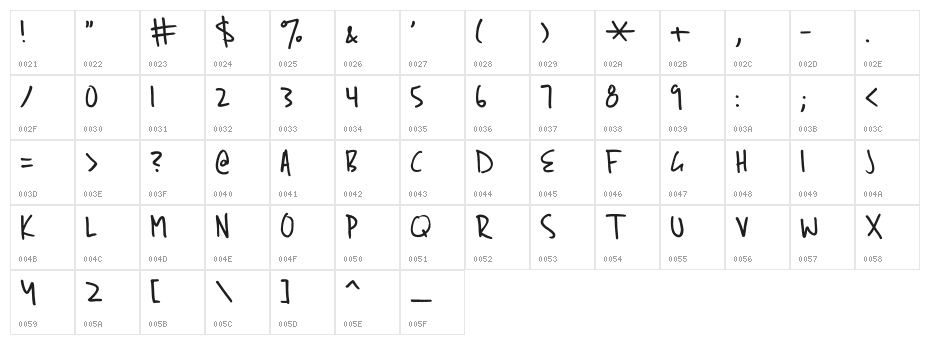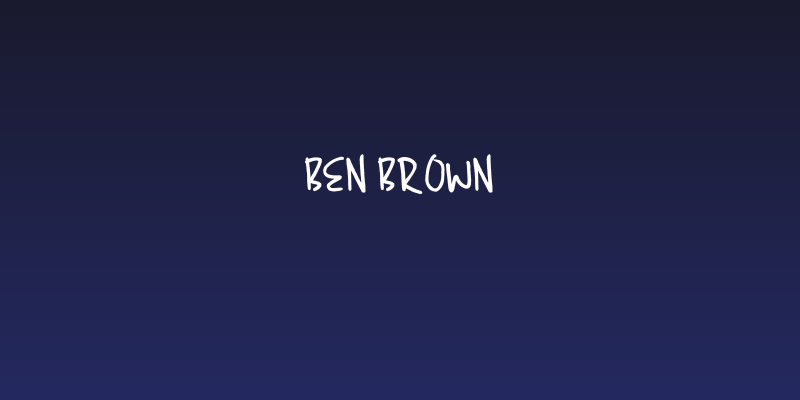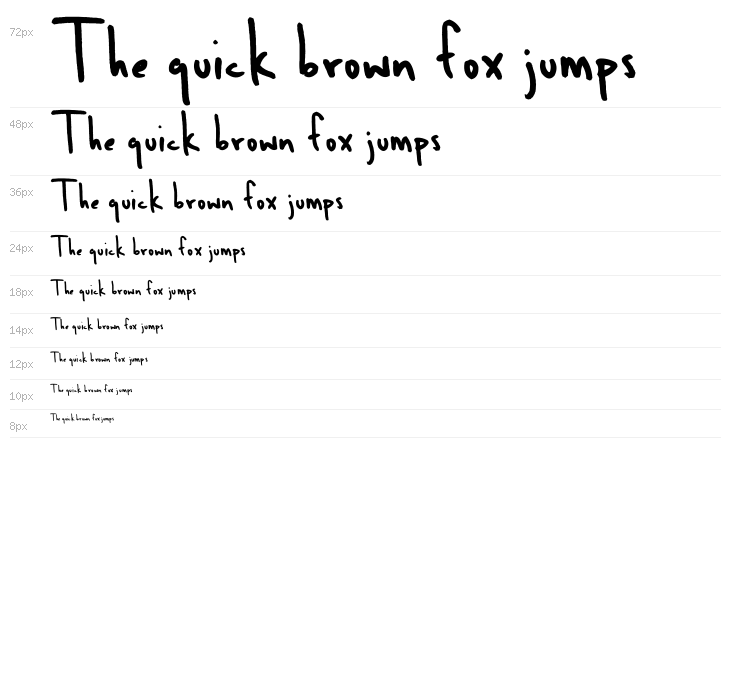
Ben Brown Font
| Stile generale | Casual, Playful |
| Caso d'uso | Headlines, Artistic projects, Personal notes |
| Progetti proposti | Ideal for invitations, greeting cards, artistic branding, and creative projects. |